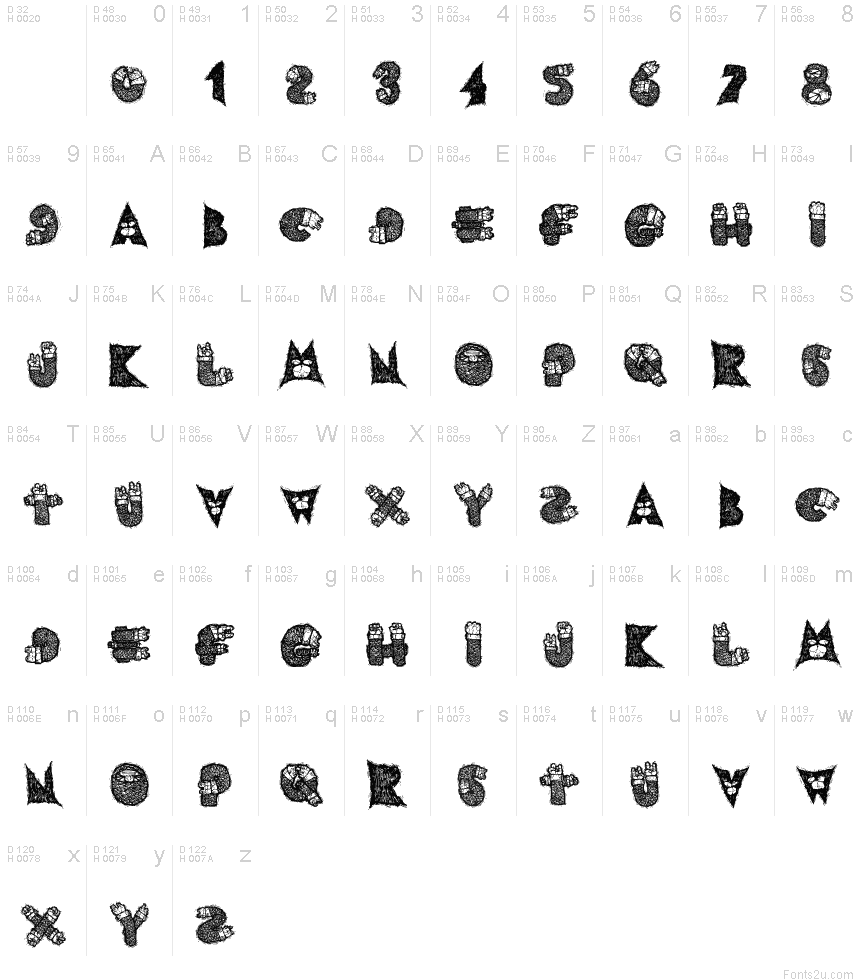
AIxDARBOTZCUMI, di Darbotz, è un font display gratuito ispirato al mondo dei graffiti e dei fumetti underground, che pullula di mostri. Le sue capitali corpose sono composte da volti affollati, occhi sbarrati, denti, scaglie e texture graffiate a mano, dando alle lettere l’aspetto di un’indisciplinata orda di creature.
Questo font gratuito è perfetto per locandine di concerti, tavole da skate, grafiche streetwear, copertine di fanzine, cover di album e brevi titoli. Usalo in grande e con parsimonia: i disegni densi all'interno invogliano a guardare da vicino, mentre le forme ampie e irregolari fanno sembrare ogni parola più un’illustrazione che una normale tipografia.